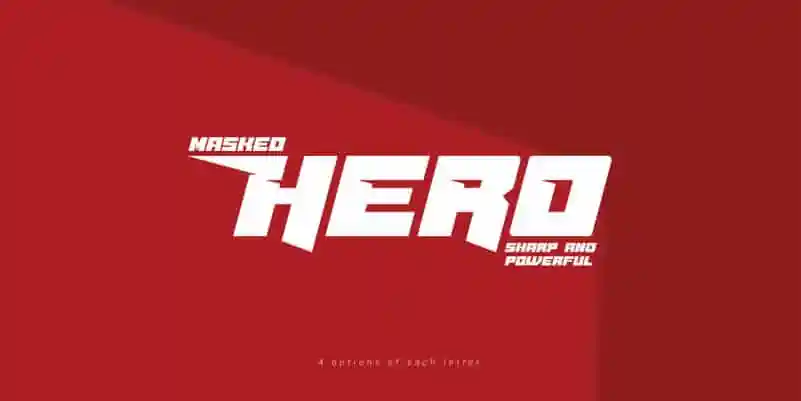
Masked Hero Display Font – Download Grátis
A “Masked Hero Display Font” é uma seleção única de letras que irá revolucionar a maneira como você compõe seu design no Brasil. Inspirada em personagens icônicos dos quadrinhos, esta fonte vem com um ar épico e vibrante, perfeita para projetos que exigem destaque visual e personalidade. Seja para criar uma HQ impactante ou dar vida a uma campanha publicitária memorável, essa fonte oferece a combinação ideal de estilo poderoso e legibilidade excepcional. Regras do designer são claras: Esta é uma fonte demo que pode ser usada apenas por propósitos pessoais. Mas para os amantes da criatividade que gostariam de apoiar o desenvolvimento futuro desta fonte, um gesto de contribuição não será perdido! Com sua elegância moderna e estilo clássico, a “Masked Hero Display Font” é uma escolha versátil que se adapta perfeitamente para projetos dos mais variados gêneros.